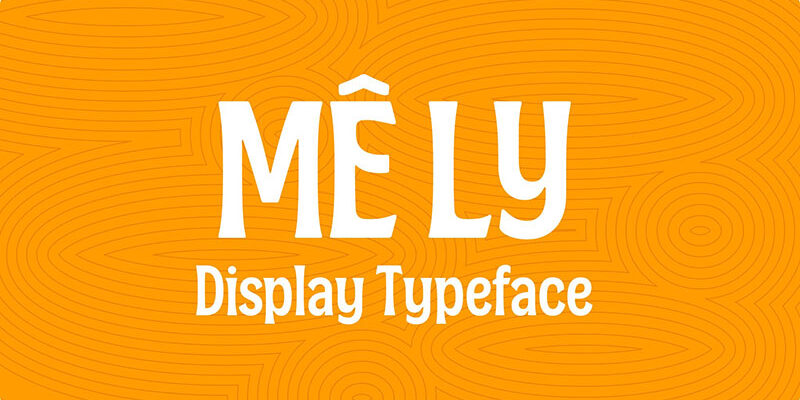
Sau thành công của CDA Independence, Cōllective Design Agency phát hành miễn phí “CDA Mê Ly Display” – bộ display font tiếng Việt được lấy cảm hứng từ những cây mơ má đào cổ thụ trên cao nguyên Mộc Châu.
Điều mang lại cảm hứng cho nhóm thiết kế không chỉ là vẻ đẹp của từng gốc mơ cổ thụ, mà là cách thiên nhiên đã âm thầm “điêu khắc” chúng qua hàng chục năm. Mỗi thân cây phình nở, mỗi nhánh cây đổi hướng, mỗi lớp vỏ chồng lên nhau đều là kết quả của thời gian, khí hậu và địa hình đặc trưng. Chính những quy luật phát triển ấy đã trở thành chất liệu để Cōllective Design Agency nghiên cứu, chuyển hóa thành bộ typeface sáng tạo mang tinh thần của thiên nhiên Việt Nam.
Những đường cong chuyển tiếp được xử lý mềm và tự nhiên hơn, tạo nên một bộ display font mang cảm giác vừa thủ công, vừa gần gũi. Mê Ly không cố gắng trở nên cầu kỳ hay phô diễn kỹ thuật; bộ chữ hướng đến sự thân thiện, dễ tiếp cận và đủ cá tính để trở thành một điểm nhấn trong các thiết kế về văn hóa, ẩm thực, nông sản hay lifestyle.